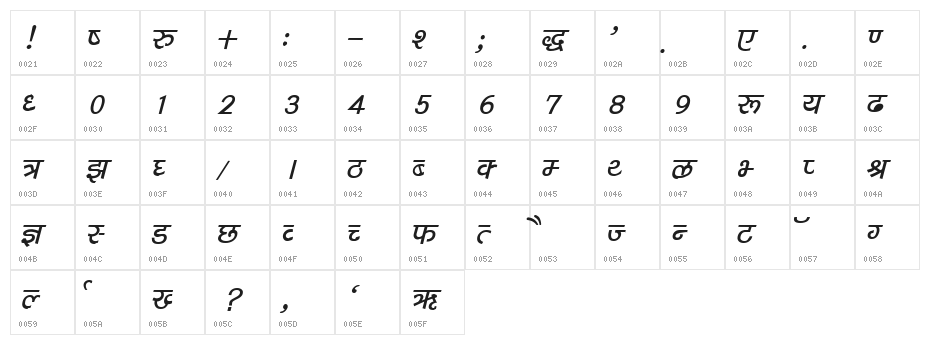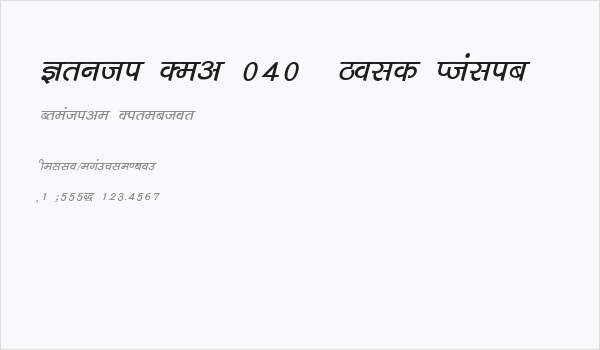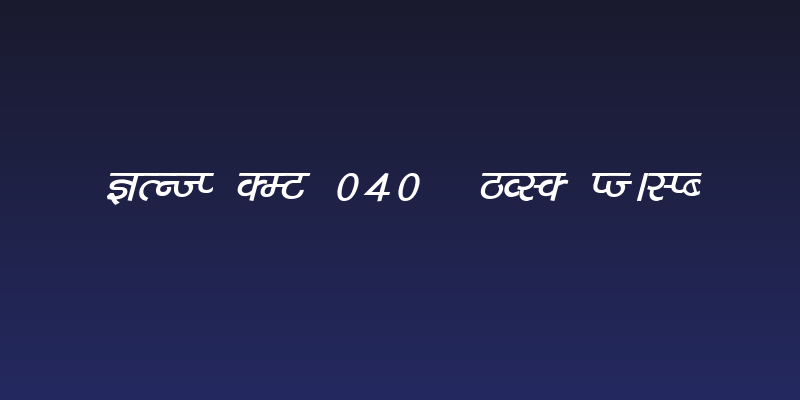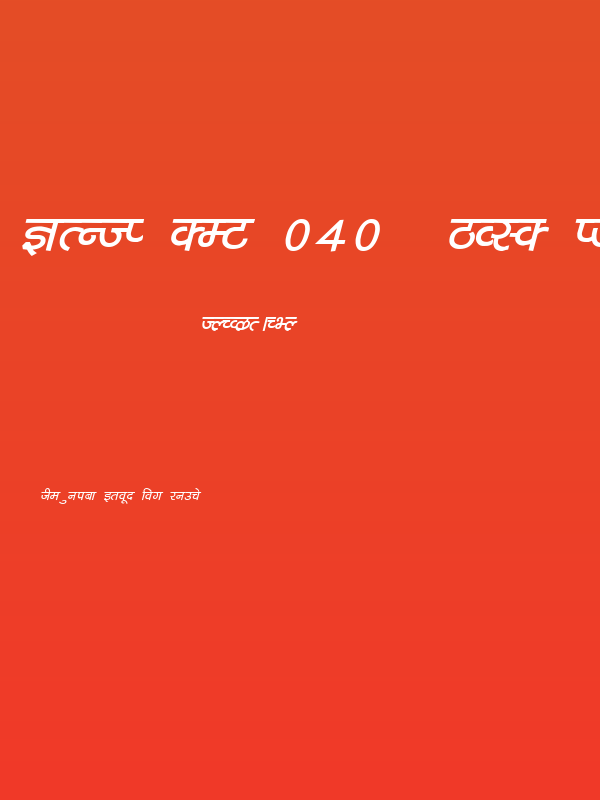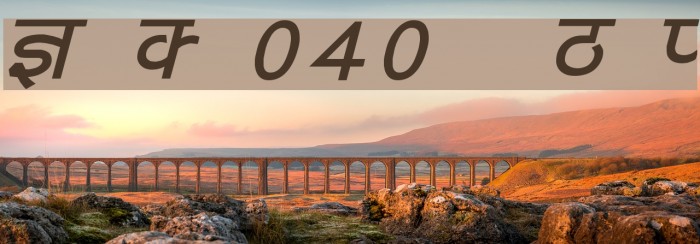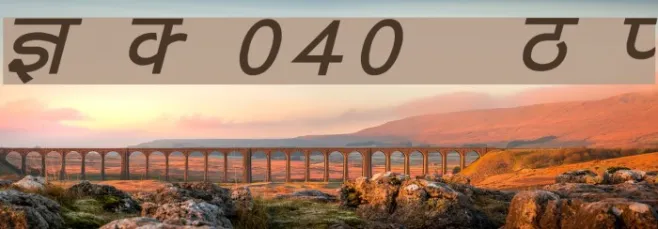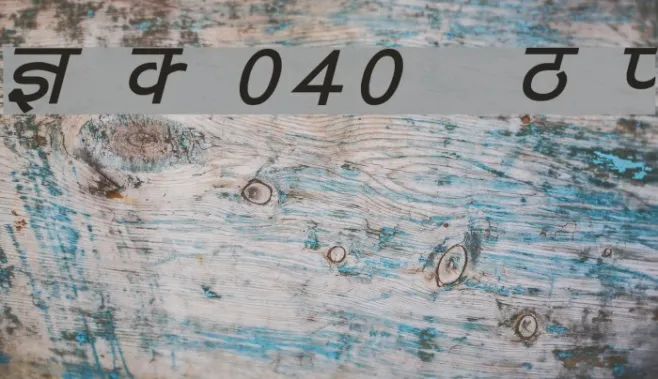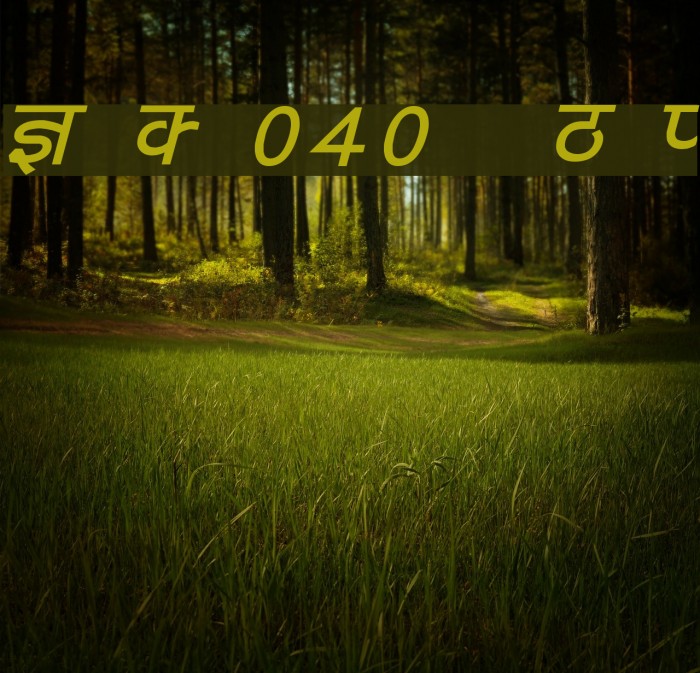
Kruti Dev 040 Bold Italic Font
Cette police comprend 197 caractères. Cliquez sur un caractère pour voir les détails.
| Cas d'utilisation | Headlines, Logos, Decorative text |
| Projets proposés | Ideal for traditional invitations, cultural event posters, and decorative headings in publications using Devanagari script. |